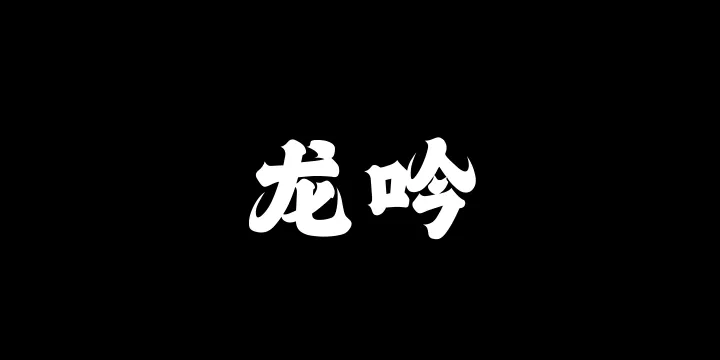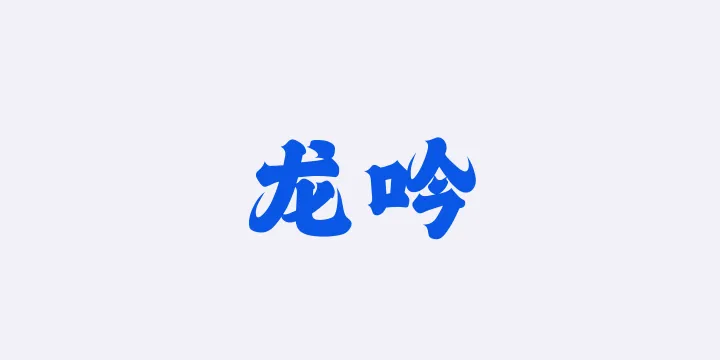
关于山海龙吟W 字体字库信息
字体全名: 山海龙吟W
字体简介: 山海龙吟,是一款全新的字体,包含汉字9169个,符号200+个。该字体狂野有力,非常醒目!字形古朴浑厚,在浑厚的同时而又极富张力,桀骜不驯的特性,霸气外露。它的笔画充满力量感,组合搭配极富强烈的节奏感。在粗细的纵横间,拥有非常规的张力特性。